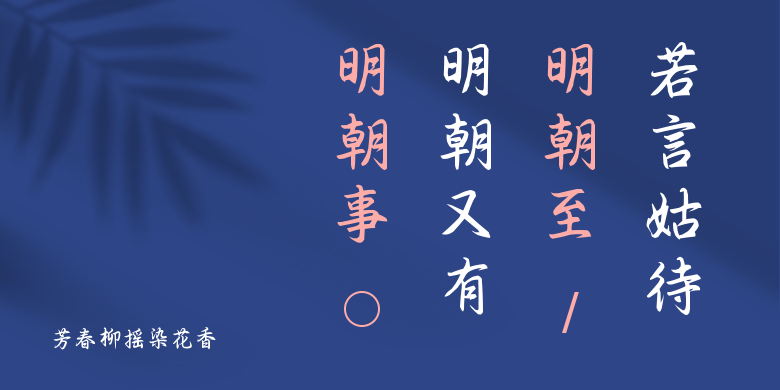
芳春柳摇染花香
芳春柳摇染花香,这款字体结构工整、笔画清晰,兼顾美观与易读性,适用于标题、正文、海报、包装、LOGO 等多种场景。字形优雅稳定,风格百搭耐看,适配日常排版与创意设计,让文字呈现更舒适、更具质感。芳春柳摇染花香一笔一画,皆是细节,以均衡的比例、流畅的线条打造舒适视觉体验,字形端正大气,风格简约现代。无论是商业设计、品牌宣传还是日常排版,都能轻松驾驭,让文字更有格调与力量。芳春柳摇染花香字体下载。